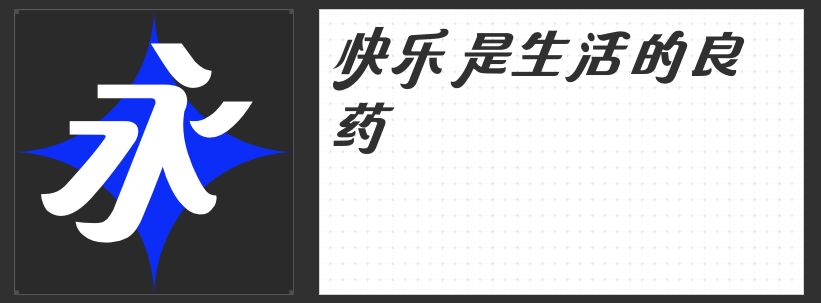
四款媒体设计优选字体:重塑视觉韵律与情感表达
在媒体设计的多元场景中,字体不仅是信息传递的载体,更是塑造视觉风格、传递情绪氛围的核心元素。以下四款字体以独特的设计语言与美学逻辑,为标题设计、版式编排及品牌视觉注入鲜活生命力,助力设计师突破常规,打造兼具功能性与艺术性的视觉作品。
1. 造字侠郝刚快乐简 微黑
这款字体以112度倾斜角打破汉字的静态平衡,将西文斜体的浪漫优雅与隶书笔画的蚕头燕尾巧妙融合。撇捺的错落变化与弧度控制,在动态中构建出斜体字的韵律感,既保留汉字的书写骨法,又赋予其轻盈跃动的视觉节奏。其微妙的平衡感使其尤其适合动态媒体设计,如短视频标题、交互界面中的动态文字,能在快速流动的信息中瞬间抓住用户注意力,传递轻松明快的情绪。
2. 励字圆梦简 中黑
以“外圆内方”为设计哲学,励字圆梦简 中黑通过直线与圆弧的对比构建视觉张力:竖折笔画替代弧线,简化结构的同时保留汉字的识别性;起笔、收笔与转折处的圆弧处理,则柔化硬朗线条,形成刚柔并济的独特气质。中宫松散的设计留出呼吸空间,避免视觉拥挤,适合长文本排版或信息密集型媒体设计,如新闻标题、杂志正文,能在保持清晰可读性的同时传递温和包容的视觉感受。
3. 励字志向黑简 中粗
针对数字媒体特性优化,励字志向黑简 中粗在黑体骨架中融入圆体元素,通过外圆角处理软化拐角锐度,既保留黑体的稳重感,又增添一丝灵动气息。字面充实、结构均衡的设计适配高分辨率屏幕,确保小字号下的清晰度与可读性,同时中粗字重赋予标题足够的视觉重量,适用于网页导航、APP图标等需要强调功能性的场景,平衡实用性与设计感。
4. 小豆岛默陌秀丽简
这款字体以传统书法为灵感,通过粗细变化的线条与疏密有致的布局,模拟毛笔书写的自然韵律。点划看似随性却暗含节奏,节点处的顿挫处理强化书写痕迹,传递出洒脱不羁的文艺气质。其强烈的个性使其成为文化类媒体设计的首选,如艺术展览海报、文学杂志封面,能瞬间营造出诗意氛围,引发观众的情感共鸣。
这四款字体以不同的美学路径回应媒体设计的核心需求,它们不仅是工具,更是设计师与受众之间的视觉桥梁。选择合适的字体,即是选择一种叙事方式,让设计在信息洪流中脱颖而出。